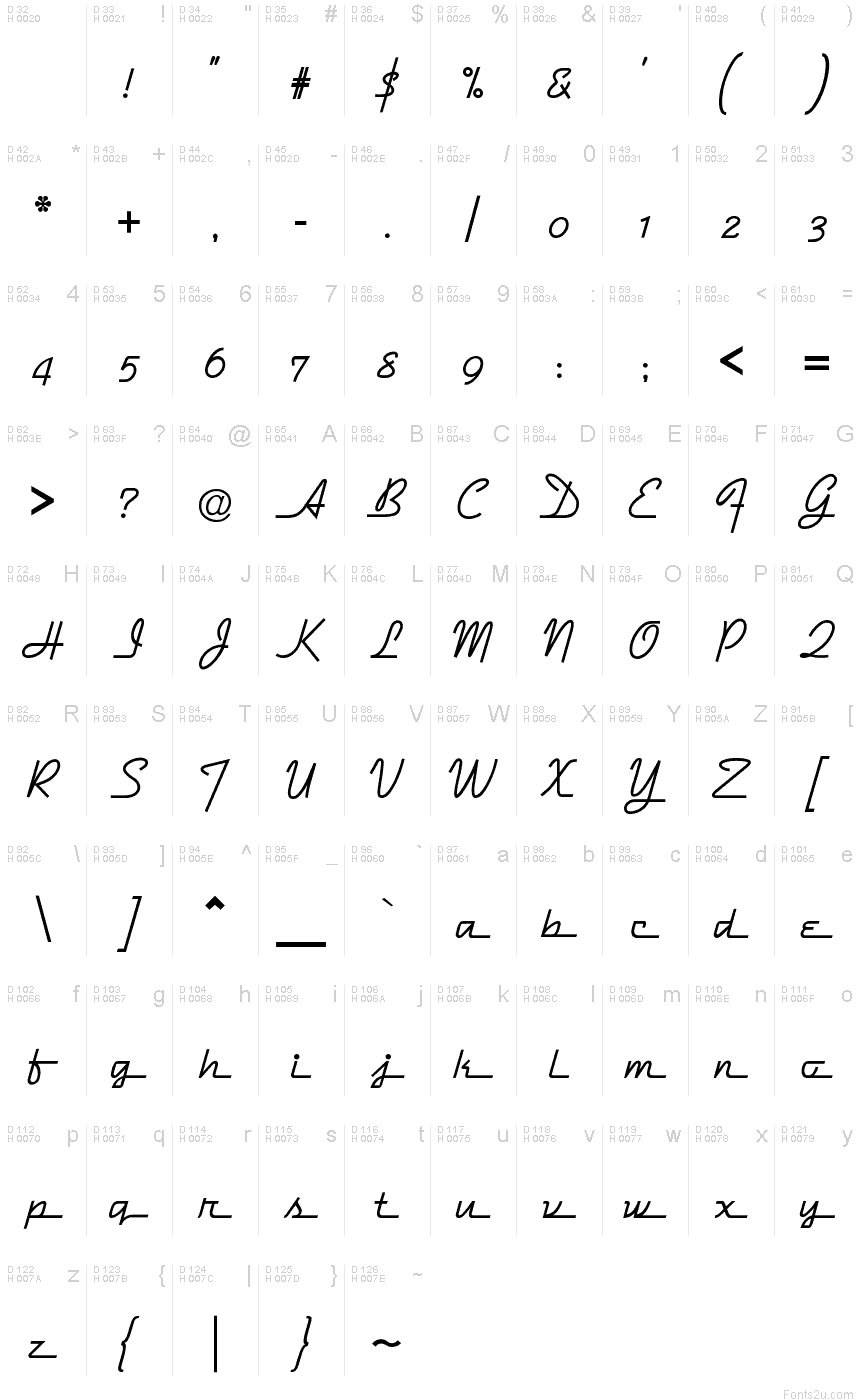
Dymaxion Script autorstwa Nicka Curtisa to płynny krój pisma odręcznego, wyróżniający się żywymi, zapętlonymi wielkimi literami oraz gładkimi, połączonymi liniami, które sprawiają wrażenie szybkiego pisma atramentem na papierze. Delikatne nachylenie i równomierna grubość znaków nadają mu swobodną pewność siebie – font pozostaje czytelny, zachowując jednocześnie osobisty i nieformalny charakter. To doskonały wybór, gdy potrzebujesz odręcznego stylu z odrobiną szlifu.
Dymaxion Script świetnie sprawdza się w podpisach, logotypach butików, zaproszeniach, kartkach okolicznościowych, opakowaniach produktów, postach w mediach społecznościowych oraz na grafikach z cytatami, gdzie liczy się swobodny, lecz stylowy wydźwięk. Ten darmowy font doskonale komponuje się z czystym krojem bezszeryfowym w mniejszym tekście, a najlepiej prezentuje się w nieco większym rozmiarze, dzięki czemu jego krzywizny i rytm mają przestrzeń, by wybrzmieć.